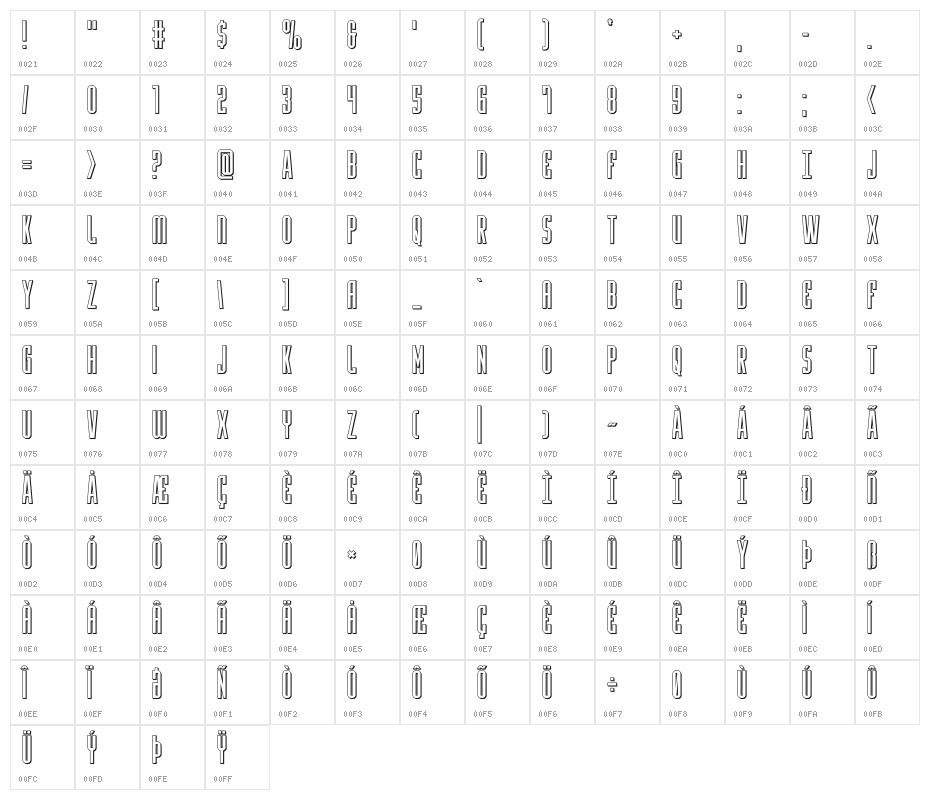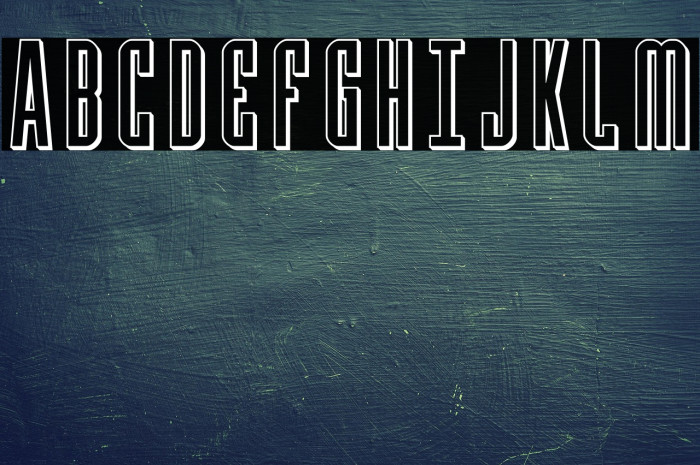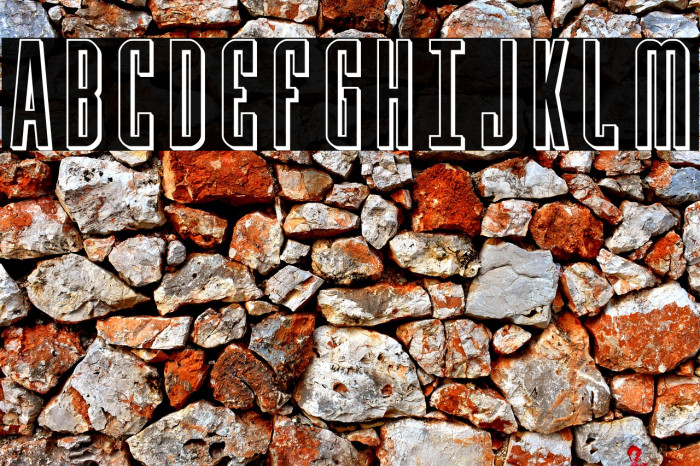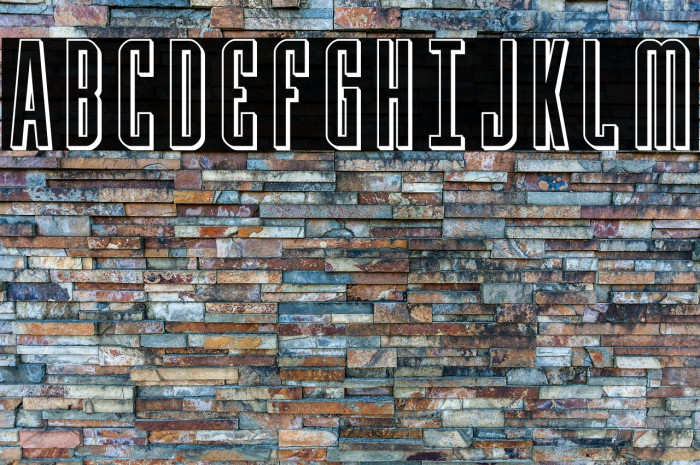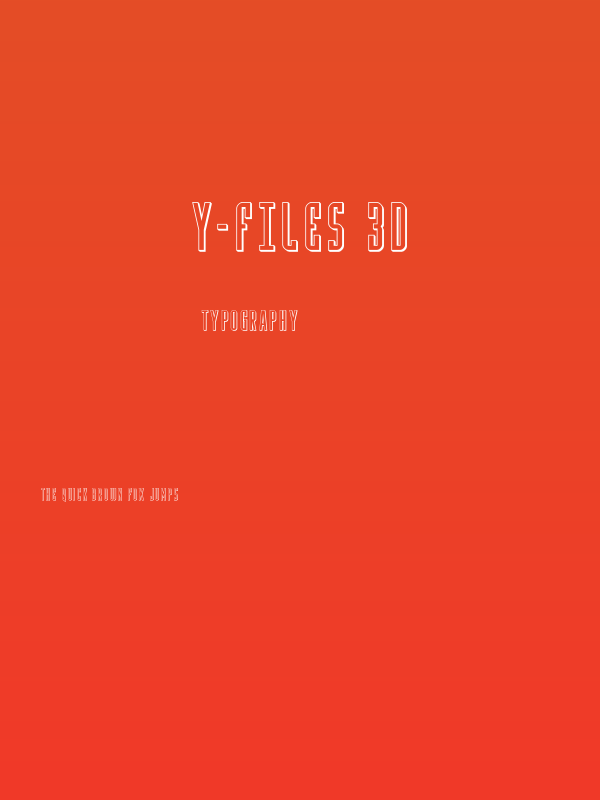
Y-Files 3D Font
| Progetti proposti | Ideal for posters, logos, and headlines where a modern, eye-catching style is desired. Suitable for branding projects that require a futuristic and bold aesthetic. |